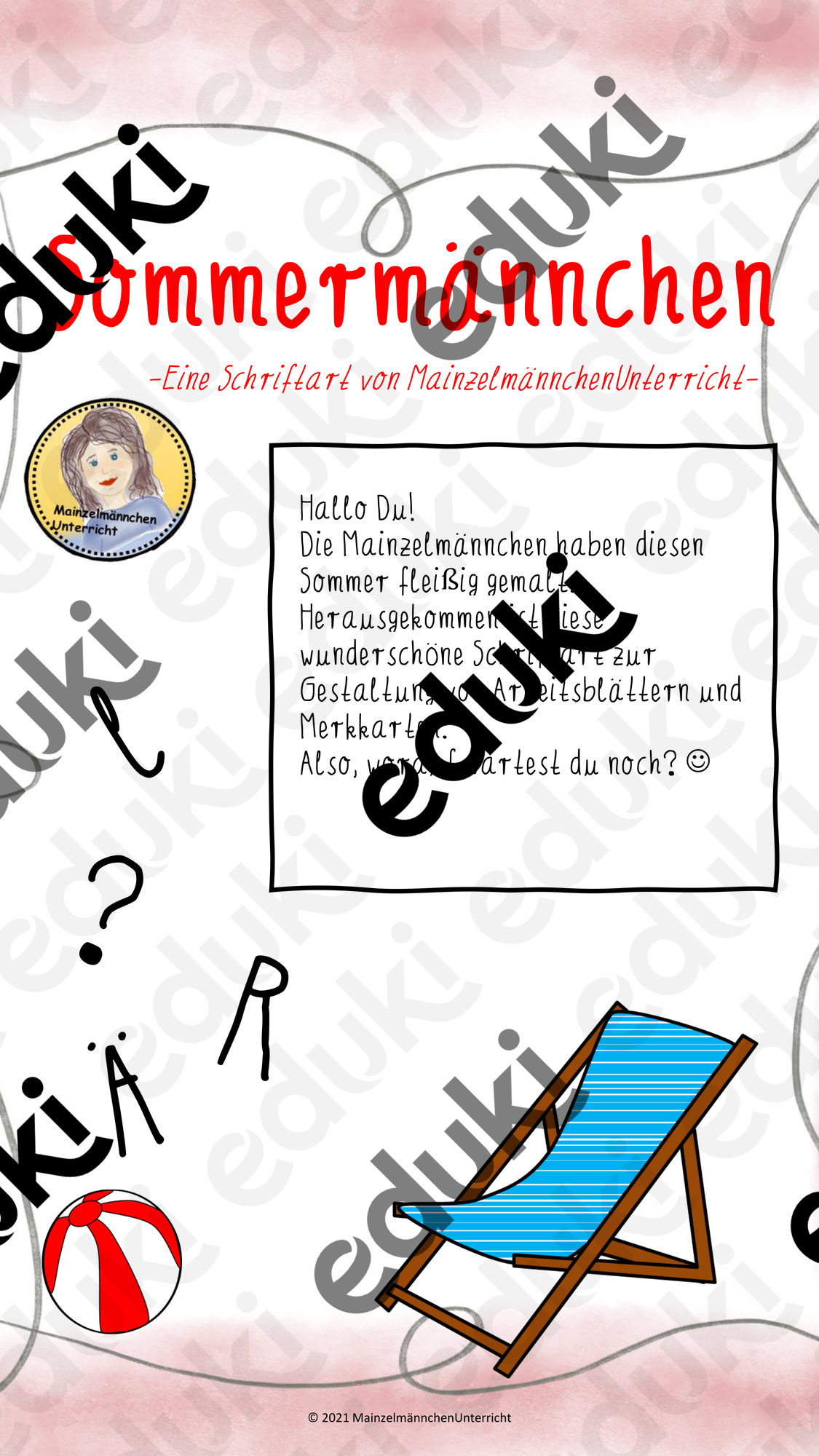
Hier findet ihr ein stetig wachsendes Paket an schönen Schriftarten zur individuellen Gestaltung von Arbeitsblättern!
Sommermännchen Font
Anbei meine lockere und sommerliche Schrift Sommermännchen mit Umlauten, Groß- und Kleinbuchstaben und den wichtigsten Satzzeichen.
Beachmännchen - ein sommerlicher Font
Schöner Font für Arbeitsblätter. Kommerzielle Nutzung erlaubt.
Märchenfee - Font
Ein verspielter Font für magische Arbeitsblätter..Kommerzielle Nutzung erlaubt :)